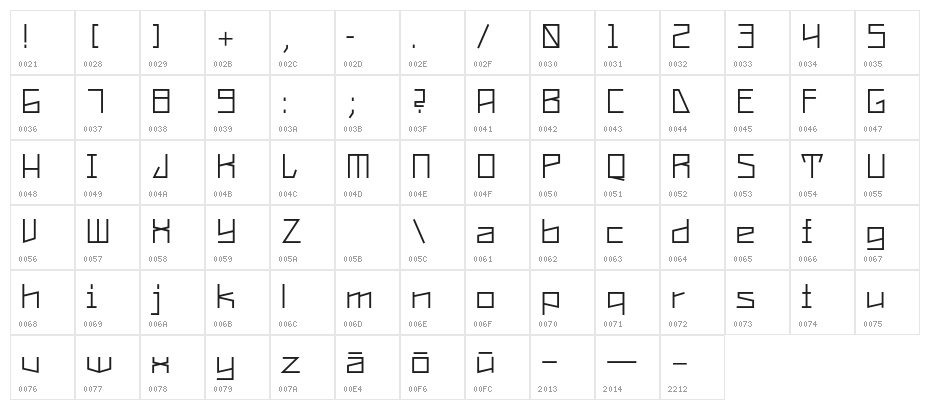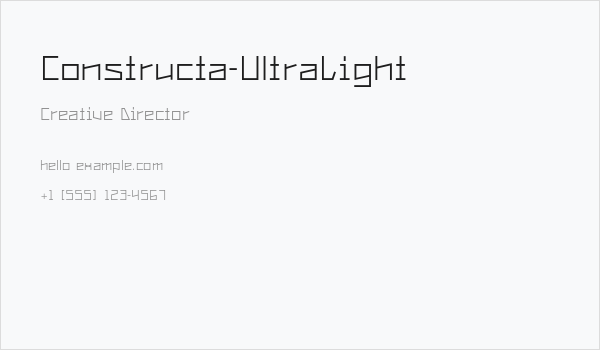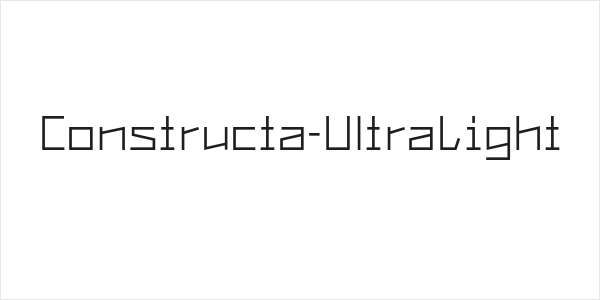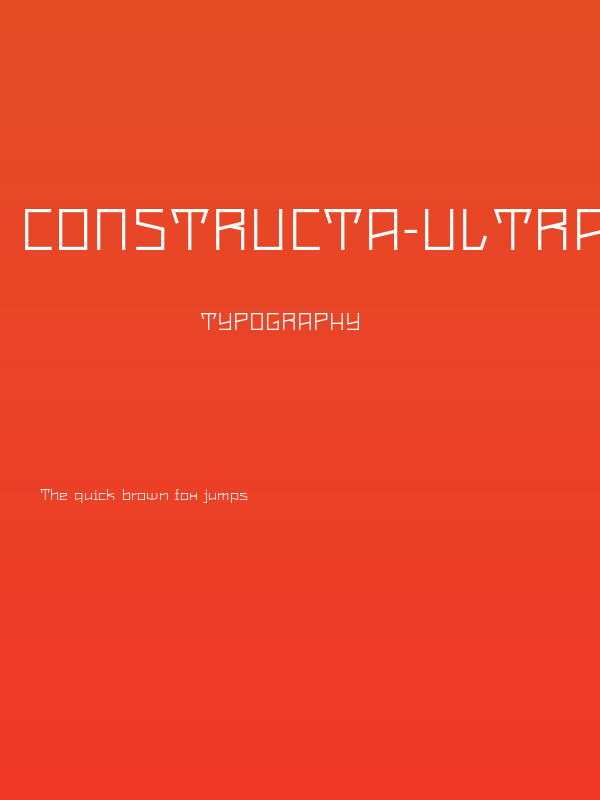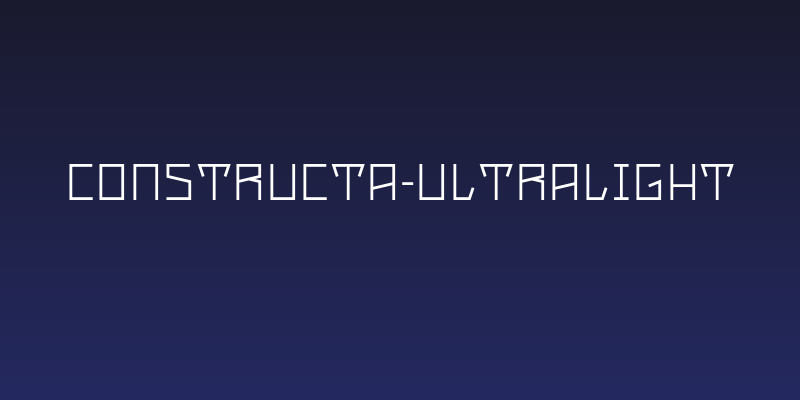
Constructa-UltraLight Font
| Caz de utilizare | Headlines, Logos, Digital interfaces |
| Proiecte propuse | Ideal for tech branding, modern posters, digital interfaces, and minimalist design projects. |